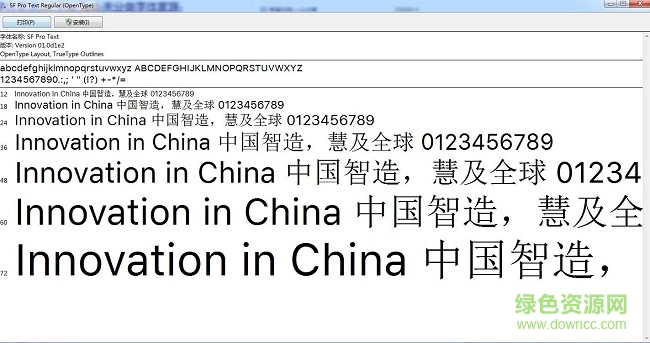
.sfnstext regular字體
.sf ns text regular字體是一款常用的英文字體,這款字體分辨率高,結(jié)構(gòu)明朗,顯示清晰,瀏覽效果非常棒,可以用在網(wǎng)頁(yè)設(shè)計(jì)中,歡迎大家免費(fèi)下載!
【Serif】
Serif在印刷學(xué)上指襯線字體,所以它應(yīng)用的最多的地方也正是出版物或者印刷品的正文內(nèi)容等以大段文字作為表現(xiàn)形式的作品上。
【sans-serif】
襯線字體以外的一切字體都是無(wú)襯線字體。無(wú)襯線字體比較圓滑,線條一般粗細(xì)均勻。比較適合用作藝術(shù)字、標(biāo)題等。